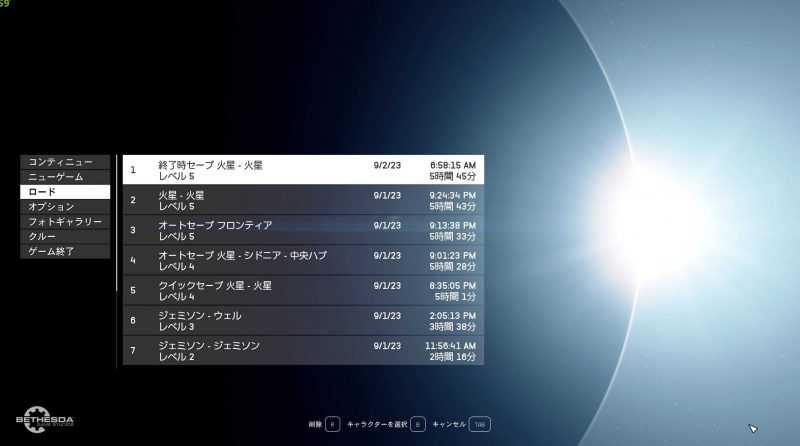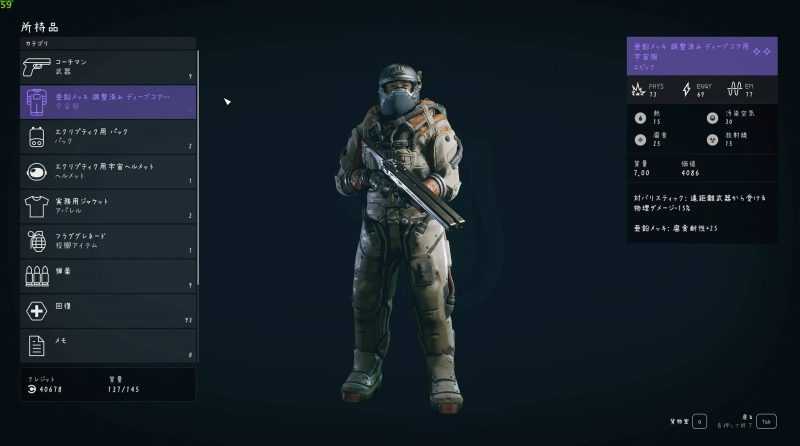
Японские шрифты anzumoji2020
<р>. Замените японский шрифт на Anzumoji 2020В исходном шрифте есть места, где все строчные буквы выражены как прописные. При изменении шрифта строчные буквы будут отображаться как строчные (например, 7,77 мм боеприпасов становится 7,77 мм)<БР>Различное изменение японского шрифта MOD<БР> (Готический) Mgen+: японские шрифты mgenplus<БР>(Шрифт Mincho ) ЖП и